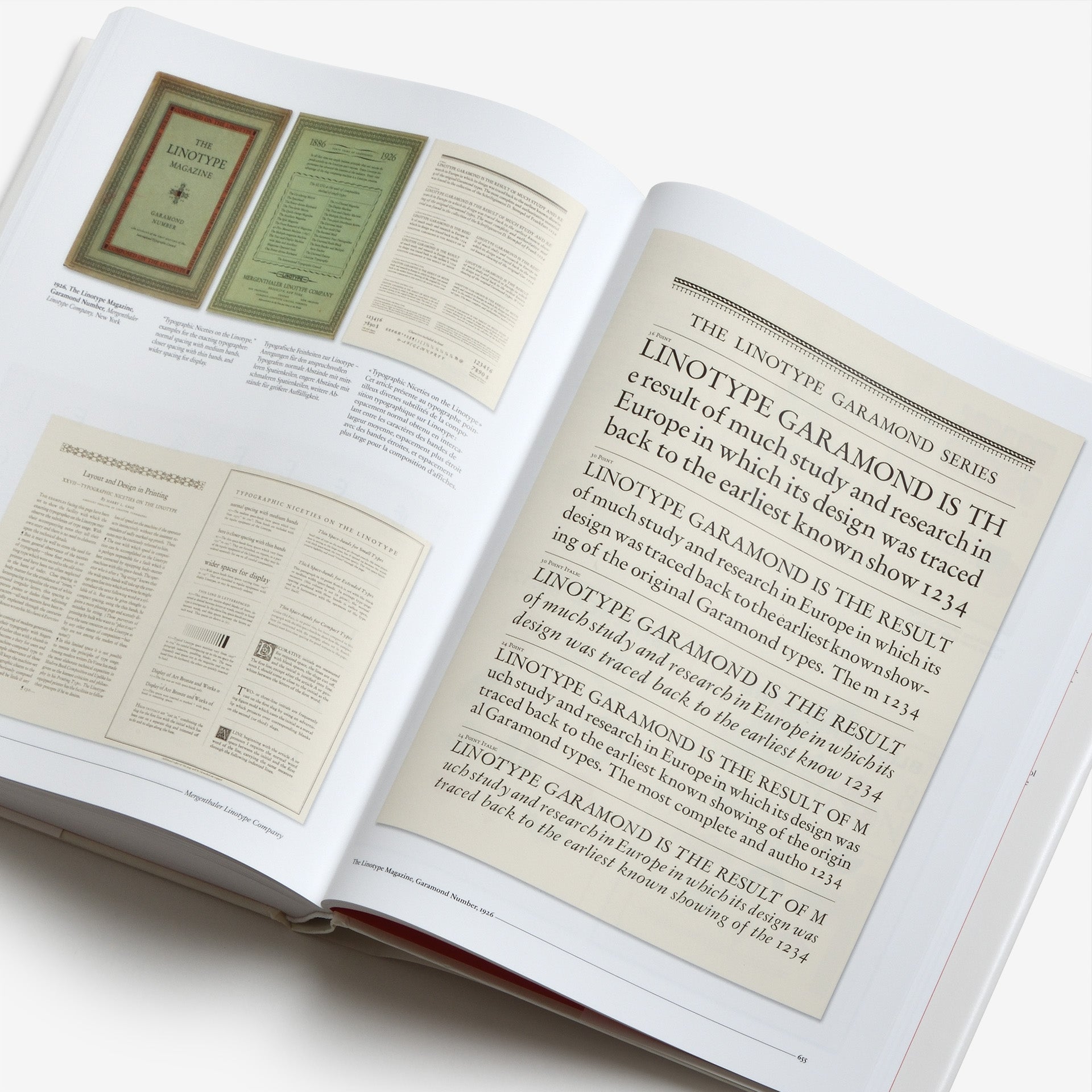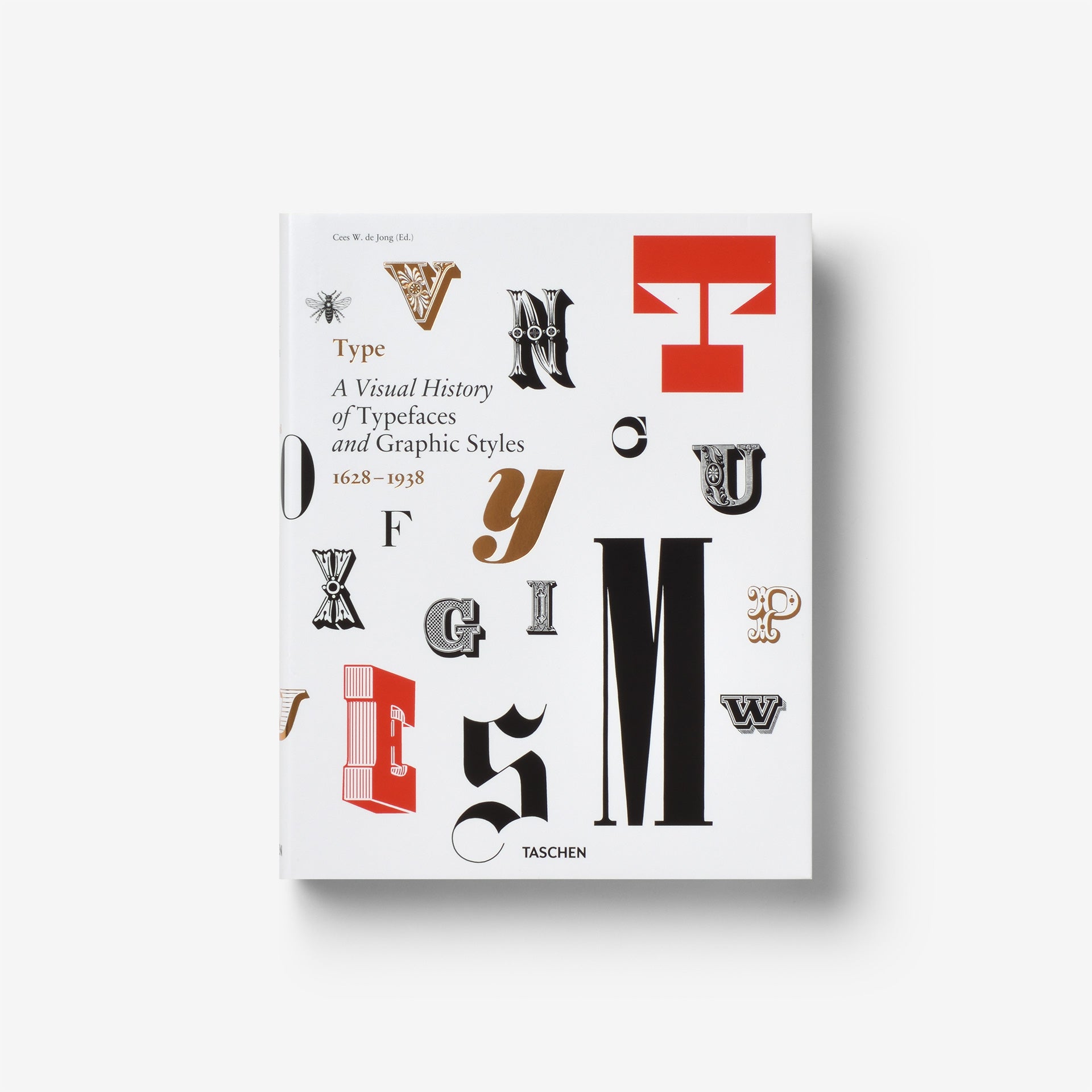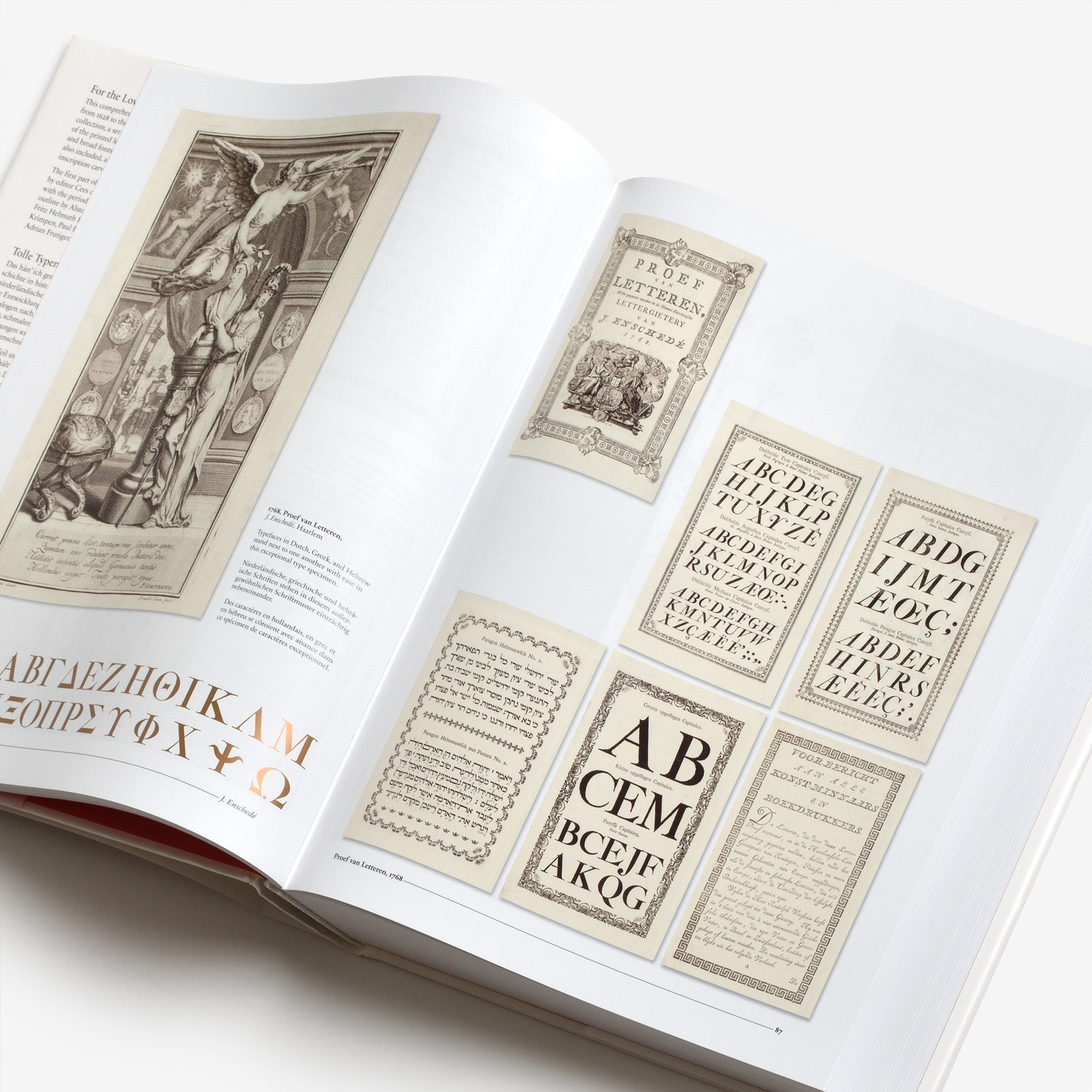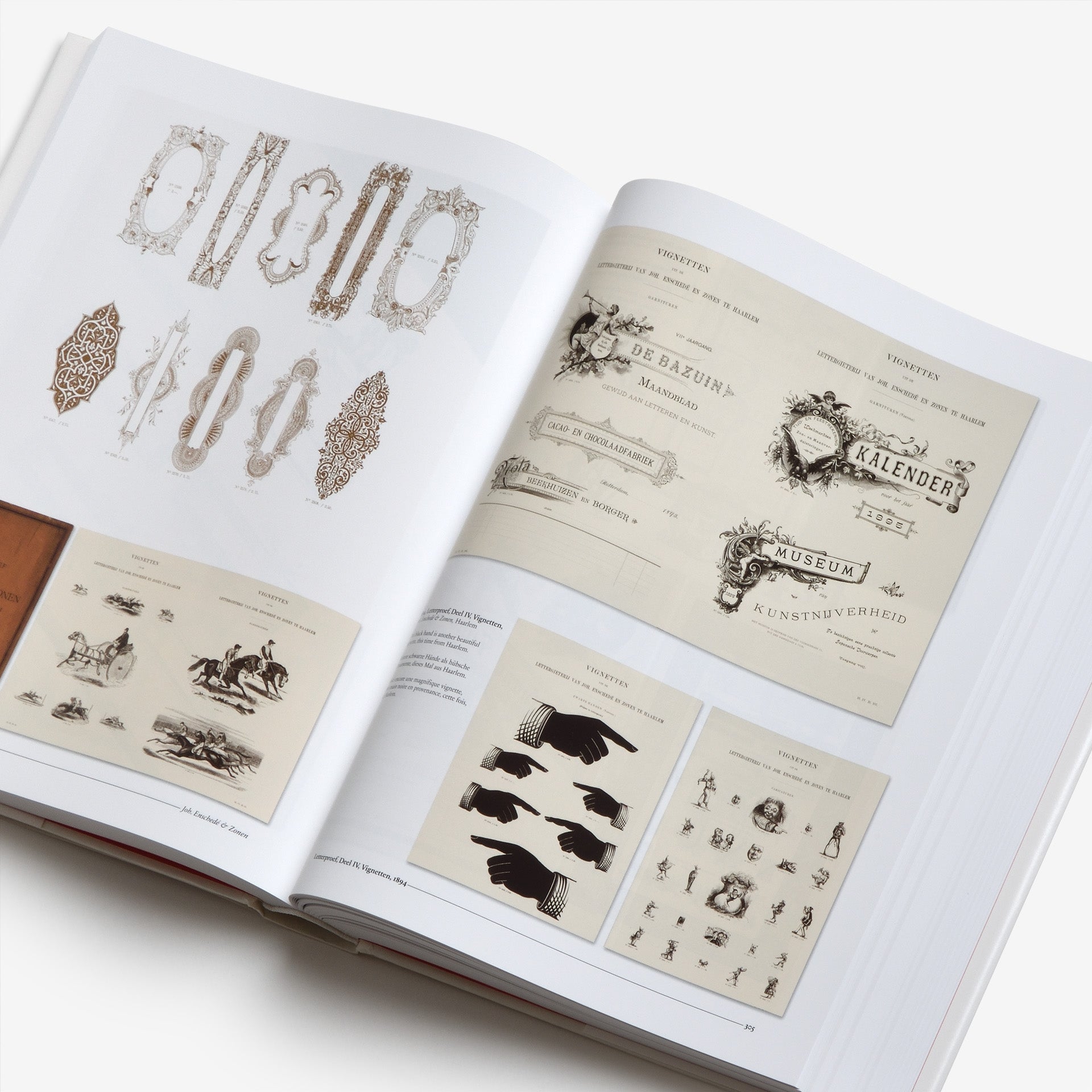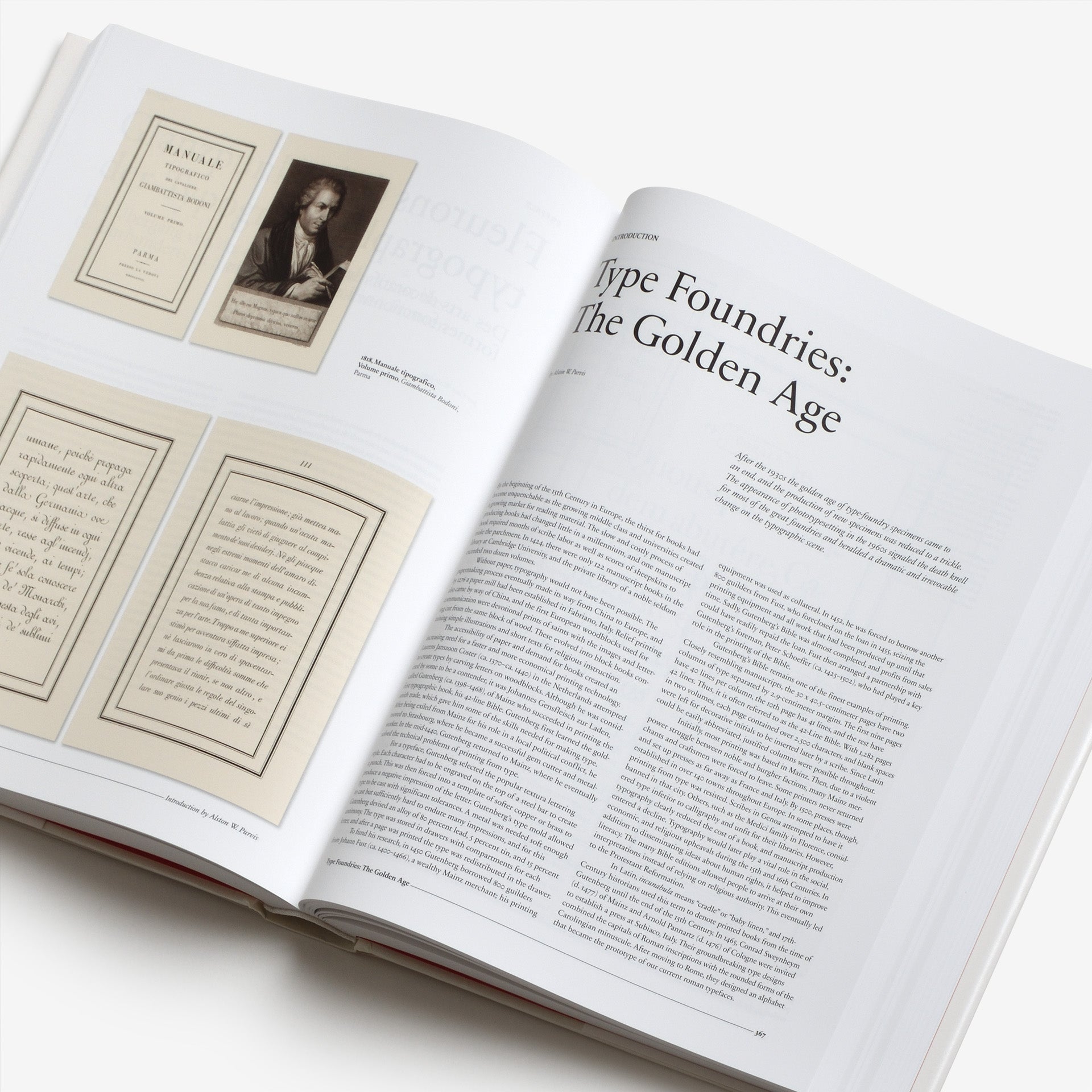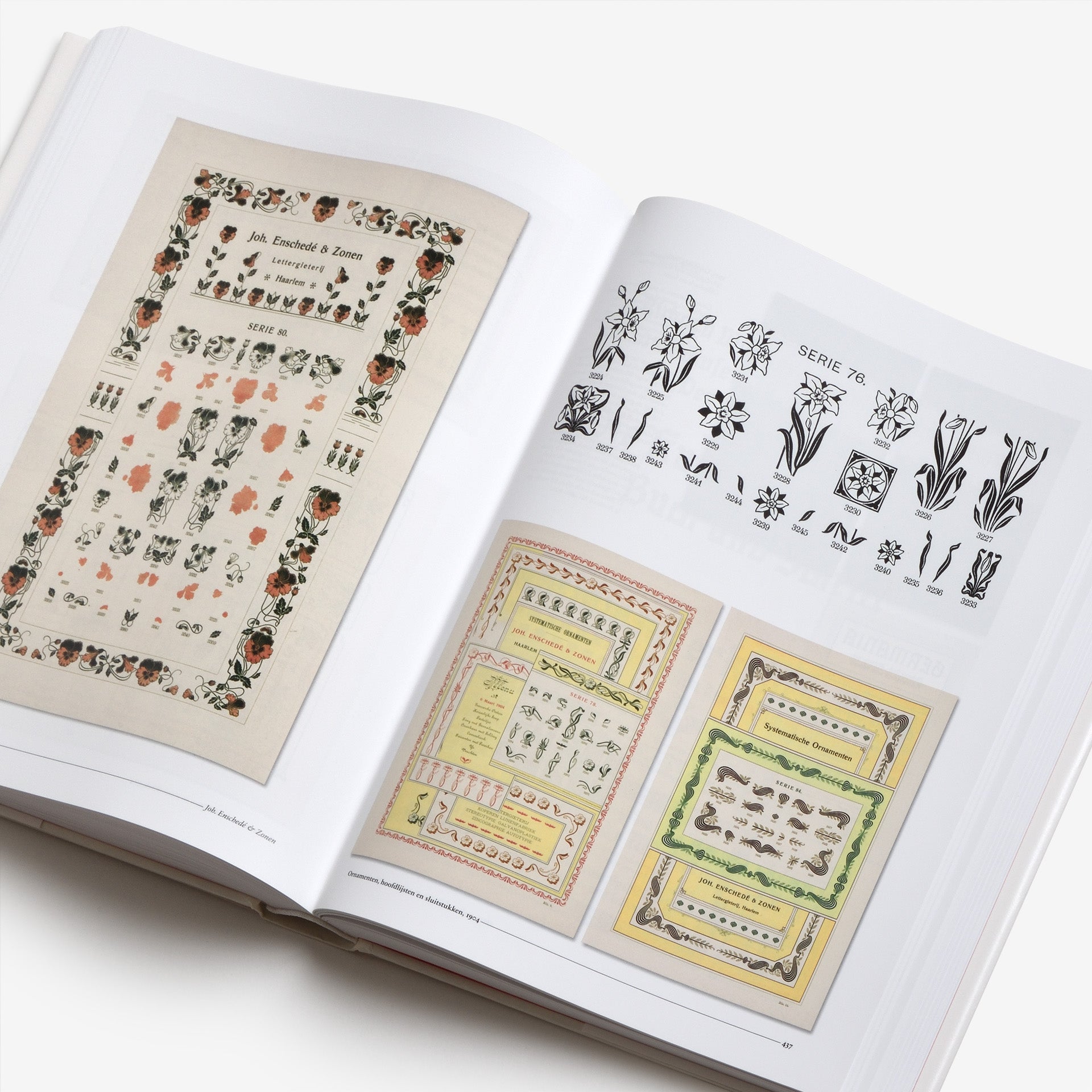
Type: A Visual History of Typefaces & Graphic Styles
Taschen
1628年から20世紀半ばまでの書体デザインを包括的に概観するコレクション。精巧にデザインされたカタログシリーズは、様々な書体見本を通して、印刷文字の進化を辿ります。装飾書体に加え、リトグラフの見本、看板作家、碑文彫刻家、カリグラファーによる書体も収録されています。
本書の前半では、編集者のセース・デ・ヨング(Cees de Jong)と収集家のヤン・ソレナー(Jan Tholenaar)によるテキストで、20世紀以前の書体を取り上げています。後半では、1900年から20世紀半ばまでの書体を取り上げ、オールストン・パービス(Alston W. Purvis)による歴史的概説を掲載しています。注目の活字デザイナーには、ウィリアム・キャスロン(William Caslon)、フリッツ・ヘルムート・エームケ(Fritz Helmuth Ehmcke)、ペーター・ベーレンス(Peter Behrens)、ルドルフ・コッホ(Rudolf Koch)、エリック・ギル(Eric Gill)、ヤン・ファン・クリンペン(Jan van Krimpen)、パウル・レナー(Paul Renner)、ヤン・チヒョルト(Jan Tschichold)、アドルフ・ムーロン・カッサンドル(A.M. Cassandre)、アルド・ノヴァレーゼ(Aldo Novarese)、アドリアン・フルティガー(Adrian Frutiger)が含まれます。